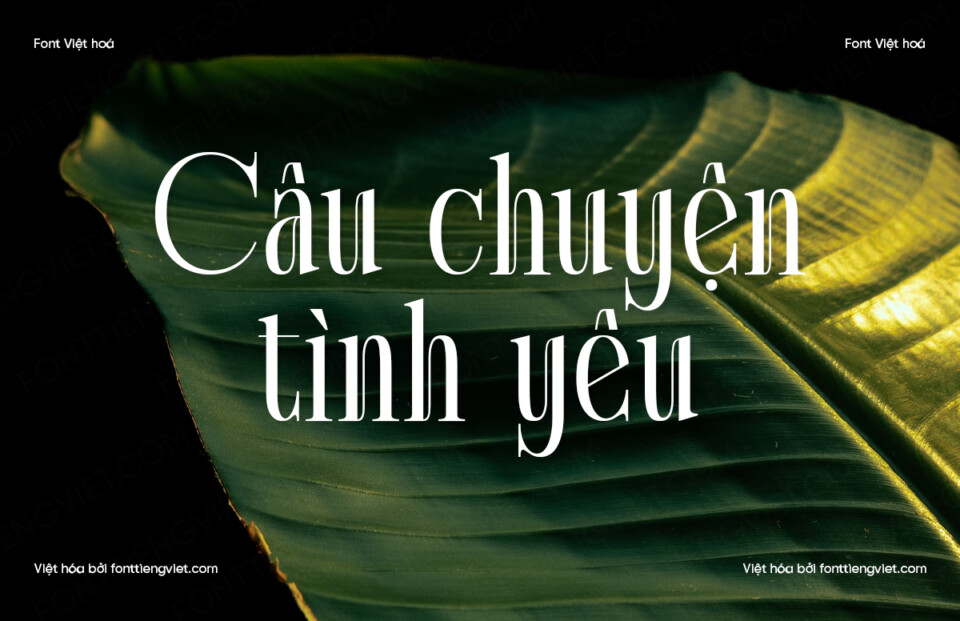
Font Việt hóa 1FTV VIP Melista Regular
Giới thiệu về Font Việt hóa 1FTV VIP Melista Regular
Trong thế giới thiết kế đồ họa hiện đại, việc lựa chọn một bộ font chữ phù hợp đóng vai trò quyết định đến linh hồn của tác phẩm. Font Việt hóa 1FTV VIP Melista Regular nổi lên như một lựa chọn hàng đầu cho những ai đang tìm kiếm sự kết hợp hoàn hảo giữa nét cổ điển và hơi thở tân thời. Đây là một định dạng Serif tinh tế, được đội ngũ 1FTV chăm chút kỹ lưỡng để tối ưu hóa hiển thị cho tiếng Việt. Với những đường nét thanh mảnh nhưng chắc chắn, bộ Font Miễn Phí này không chỉ đáp ứng tốt yêu cầu về mặt thẩm mỹ mà còn đảm bảo tính dễ đọc trên nhiều nền tảng khác nhau từ in ấn đến hiển thị kỹ thuật số.
Đặc điểm nổi bật của Melista Regular
Lý do khiến Font Việt hóa 1FTV VIP Melista Regular trở nên đặc biệt nằm ở cấu trúc chữ cái cân đối và các chi tiết uốn lượn đầy nghệ thuật. Các dấu tiếng Việt được đặt ở vị trí chuẩn xác, không gây cảm giác rời rạc hay lỗi font khi soạn thảo văn bản dài. Điều này cực kỳ quan trọng đối với các nhà thiết kế Việt Nam khi muốn truyền tải thông điệp một cách trọn vẹn và chuyên nghiệp nhất.
Ứng dụng thực tế của Font Việt hóa 1FTV VIP Melista Regular
Bộ font này cực kỳ đa năng và có thể áp dụng vào nhiều dự án khác nhau. Đối với các bạn học sinh và sinh viên, đây là công cụ đắc lực để trang trí bài thuyết trình, làm báo cáo thực tập hoặc thiết kế thiệp mời cho các sự kiện trường lớp. Trong khi đó, các nhà thiết kế chuyên nghiệp thường sử dụng nó cho các bộ nhận diện thương hiệu cao cấp như mỹ phẩm, thời trang hoặc menu nhà hàng sang trọng.
Sử dụng trong thiết kế Branding và Logo
Nhờ vẻ ngoài lịch lãm, Font Việt hóa 1FTV VIP Melista Regular giúp thương hiệu khẳng định được đẳng cấp và sự tin cậy. Khi kết hợp với các khoảng trắng hợp lý, font chữ này tạo ra một không gian thị giác thoáng đãng, giúp người xem tập trung vào nội dung chính mà không cảm thấy bị rối mắt. Bạn có thể sử dụng nó cho tiêu đề chính (headline) hoặc các đoạn trích dẫn quan trọng để tạo điểm nhấn thị giác mạnh mẽ.
Tối ưu hóa trải nghiệm người dùng trên Website
Không chỉ dừng lại ở đồ họa tĩnh, font chữ này còn hoạt động mượt mà trên các giao diện web. Độ tương phản giữa các nét thanh và nét đậm được tinh chỉnh giúp văn bản hiển thị sắc nét trên cả màn hình điện thoại di động và máy tính để bàn. Việc sử dụng một bộ font đã được Việt hóa giúp website của bạn trông đồng bộ và chuyên nghiệp hơn trong mắt khách hàng Việt.
Kết luận về bộ font chữ độc đáo